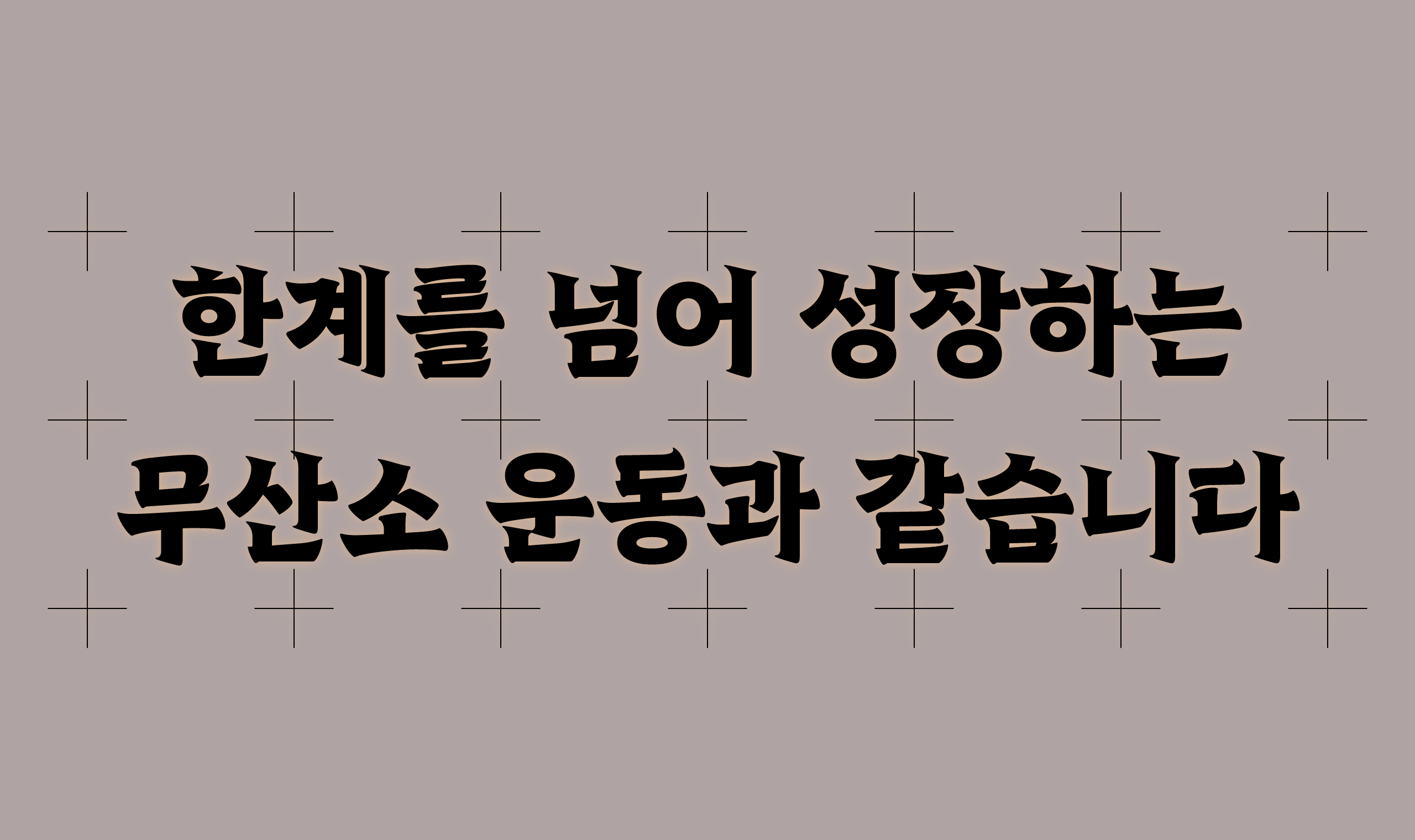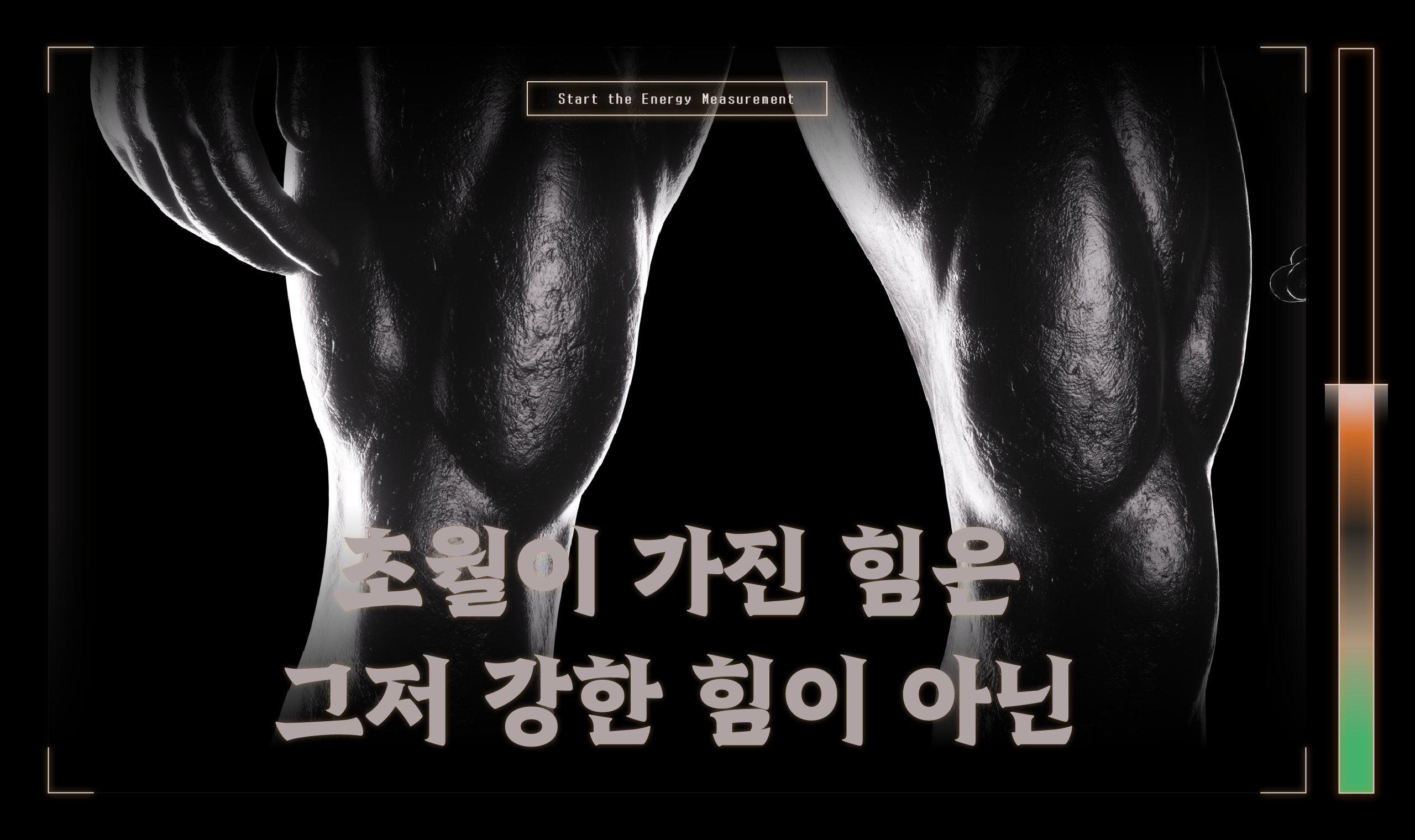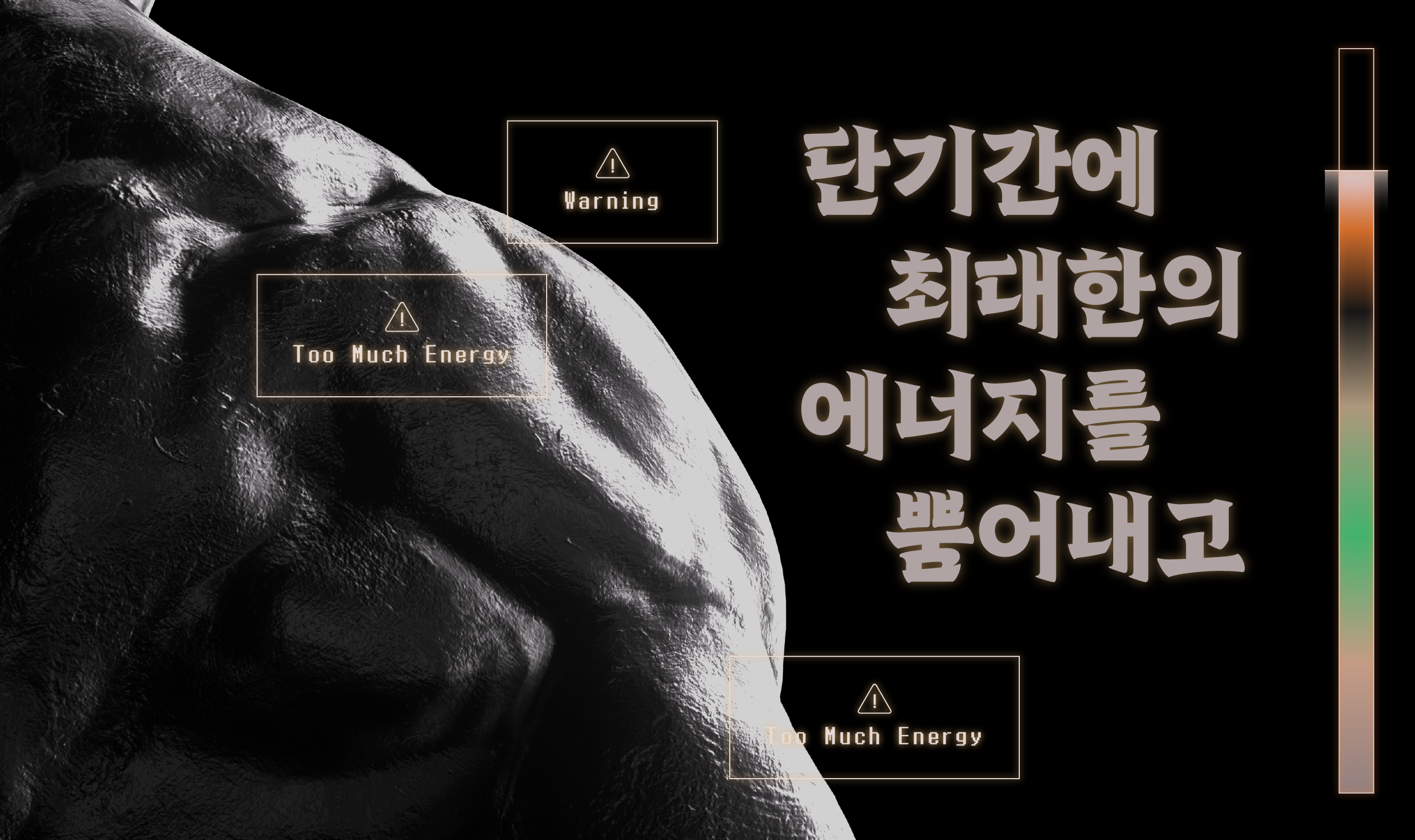
초월
Yoon 초월
'초월'은 한계를 뛰어넘은 힘이 느껴지는 서체입니다. 초월이 가진 힘은 그저 강한 힘이 아닌, 단기간에 최대한의 에너지를 뿜어내고 한계를 넘어 성장하는 무산소 운동과 같습니다. 마치 에너지가 폭발할 듯한 강한 퍼포먼스가 필요할 때 초월을 사용해 보세요.